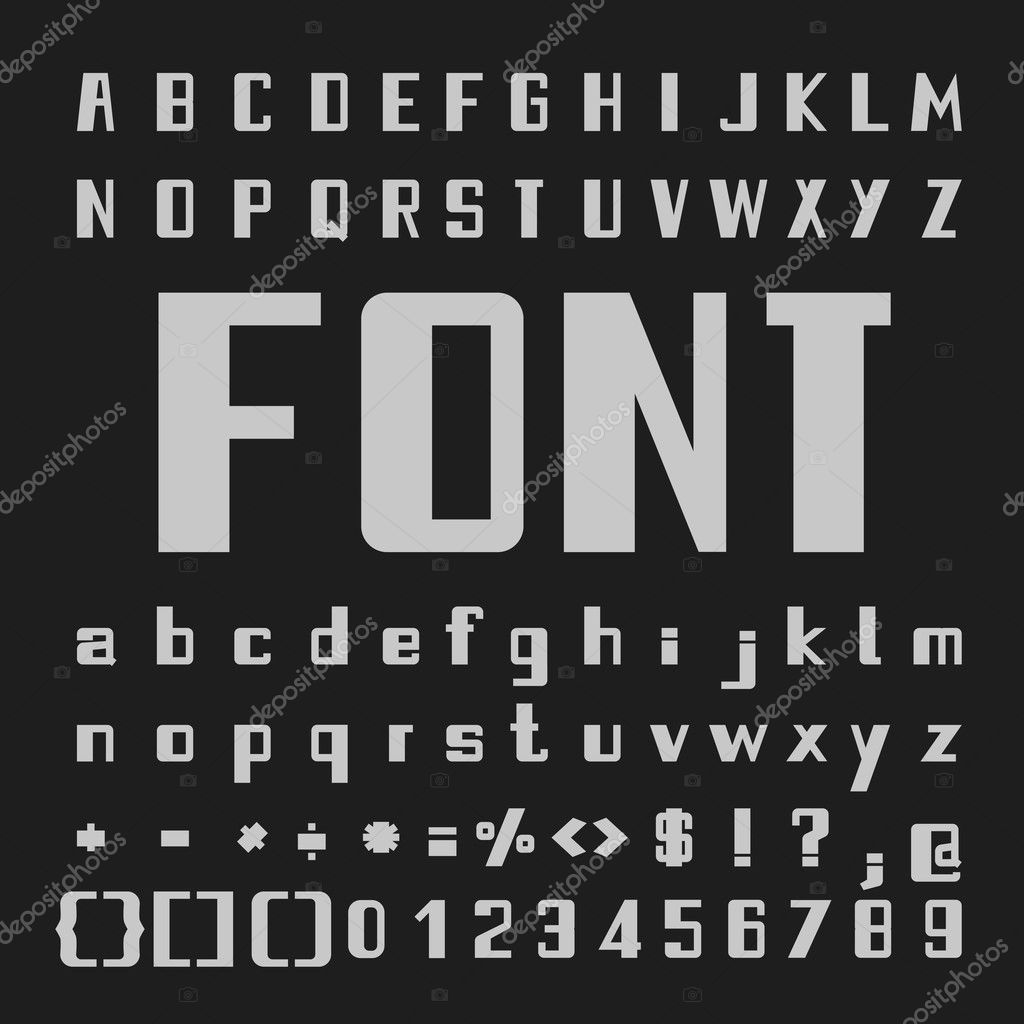
7 типов особо жирных шрифтов (с примерами)
Хотите привлечь внимание зрителей своим следующим дизайном и дать им пощечину? Если это так, то тонкие, вежливые шрифты, вероятно, не справятся с этой задачей. Вместо этого толстые, массивные шрифты, привлекающие внимание, могут помочь.
Эти шрифты специально разработаны для дизайнеров, которые не боятся рисковать, отклоняясь от традиционных тенденций дизайна. Таким образом, если вы думаете, что готовы пойти на такой риск, рассмотрите возможность использования любого из следующих сверхжирных шрифтов в своем следующем проекте.
1. Высококонтрастный
Многие полужирные шрифты характеризуются неизменным размером штриха. Вы можете использовать забавный шрифт, который мы проиллюстрировали выше, в качестве примера. Вы заметите, что все буквы имеют одинаковый размер штриха. Тем не менее, это может быть не ваш желаемый вариант.
Если вы ищете немного более контрастный шрифт в предстоящем проекте, выберите один из следующих высококонтрастных шрифтов, которые мы указали ниже.
Штрихи в этих шрифтах, варьирующиеся от очень толстых до ультратонких, делают их очень популярными. Это потому, что они не только производят впечатление визуально, но и источают «ощущение» изящества и класса. Риск не означает, что вы не можете сделать это стильно!
Варианты шрифтов:
Nouvelle Vague
Bodoni XT
2. Жирный и компактный
Недостатком слишком жирных шрифтов является то, сколько места они обычно занимают. Если вы работаете над проектом компактного дизайна, но все еще хотите заявить о себе с помощью жирного шрифта, один из следующих жирных и компактных вариантов может быть идеальным вариантом.
Будучи очень смелыми, но занимающими меньше места, они предлагают лучшее из обоих миров. Вы заметите, что в приведенном ниже примере штрихи все еще очень темные и производят впечатление, но поскольку они сгущены, вы можете разместить их в труднодоступных местах. Просто будьте осторожны, не злоупотребляйте им, потому что это может привести к тому, что ваше пространство будет выглядеть загроможденным и тесным, если вы переборщите.
И для большинства людей чтение страниц, выделенных жирным шрифтом, само по себе тяжело для глаз, поэтому сжатые шрифты делают это еще труднее. Скорее всего, если вы переборщите, они в конечном итоге пропустят что-то важное.
Варианты шрифтов:
Archery
Furore
Hursheys
Forque 9001 6
3. Винтаж
Иногда винтаж и смелость просто лучше. По крайней мере, это предположение с этими шрифтами. Если вы хотите передать ощущение ретро, используйте один из следующих шрифтов для впечатляющего результата. Они отлично подходят для включения «эмоций» в дизайн.
Например, «страшное» ощущение, которое часто изображают эти старомодные постеры фильмов. Или изящное вычурное чувство, которое вы можете найти в рекламе музея. В любое время, когда вы хотите добавить немного «старой школы» в свой проект, винтажные шрифты — отличный способ сделать это.
Варианты шрифтов:
Vintage
Candy Inc
Superstar
4.
Игривый 9000 2 Несмотря на то, что очень жирный шрифт часто выглядит громким, он не обязательно должен быть оскорбительным или даже стильным, изящным, или ретро. Иногда они просто хотят повеселиться! Если вы хотите сохранить игривое ощущение в своих проектах, рассмотрите возможность использования одного из следующих игривых полужирных шрифтов. Эти шрифты — отличный вариант для дизайна, ориентированного на детей, или более спокойных проектов.Они немного напоминают пряники и фрески улицы Сезам. Вы также найдете эти шрифты, используемые в дизайне упаковки многих популярных сегодня игрушек и другой рекламы, ориентированной на молодежь и подростков.
Предложения шрифтов:
Cookies
Grobold
Bubblegum
5. Heavy и Sans Serif 900 07
Следующие шрифты тяжелые, черные и современные. Они также отлично подходят для достижения эффекта на вашем лице. Используйте эти параметры, если хотите произвести впечатляющее впечатление с помощью современного подхода без засечек.
Вы также можете попробовать скомбинировать шрифт без засечек (шрифт без ножек) со шрифтом с засечками (шрифт со стопами) и немного смешиваем.
Смешивать и сочетать шрифты может быть немного опасно, и результат может в конечном итоге выглядеть любительским, поэтому немного поэкспериментируйте, и я бы рекомендовал всегда получать второе мнение, прежде чем приступать к любому дизайну проекта.
Предложения шрифтов:
Harabara
Bebas Neue
Boris Black Boxx
6. Serif Bold
Возможно, шрифт без засечек — не тот путь, который вам нужен. Следующие варианты шрифтов предназначены для тех традиционалистов, которые любят хороший шрифт с засечками. Сочетание смелых штрихов и элегантных деталей с засечками может стать отличным вариантом для вашего следующего проекта.
Помните, что шрифты с засечками — это шрифты с «ножками» (или небольшими деталями в нижней части каждой буквы, которые немного расширяются) , и иногда их можно комбинировать с аналогичными шрифтами без засечек для получения отличного эффекта, часто «старомодного».
вылеплен» по настроению.
Предложения шрифтов:
Grendel
Bambi